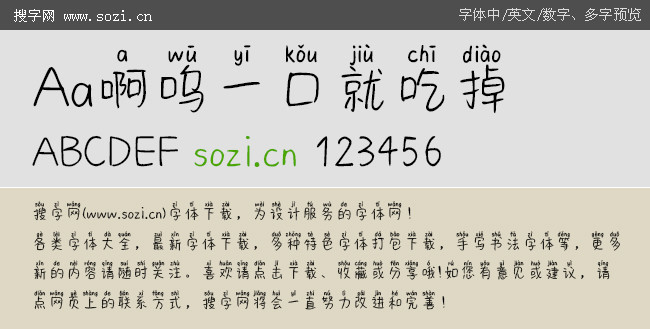
Aa啊嗚一口就吃掉字體
搜字網(wǎng)給大家提供一款A(yù)a啊嗚一口就吃掉字體中文卡通字體下載,這是一款手寫風(fēng)格的卡通字體,充滿童趣,非常可愛,適合手機(jī)顯示使用、卡通畫冊、兒童用品宣傳廣告等應(yīng)用(此字體為個人非商用版,如需商用請聯(lián)系作者購買版權(quán))。